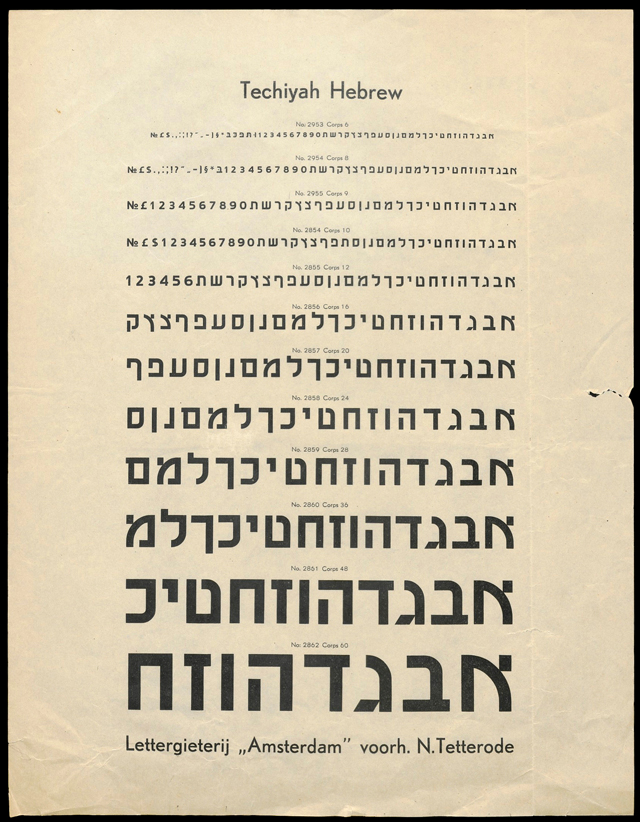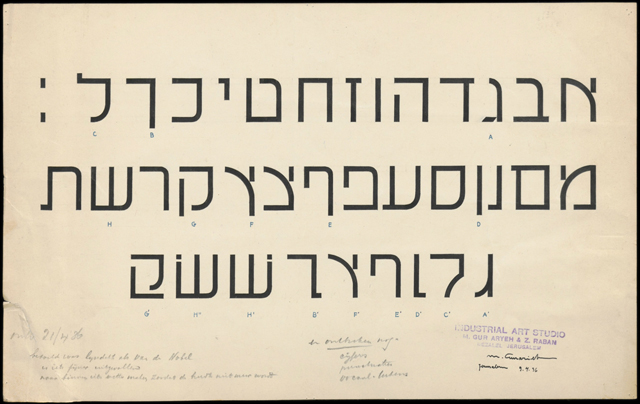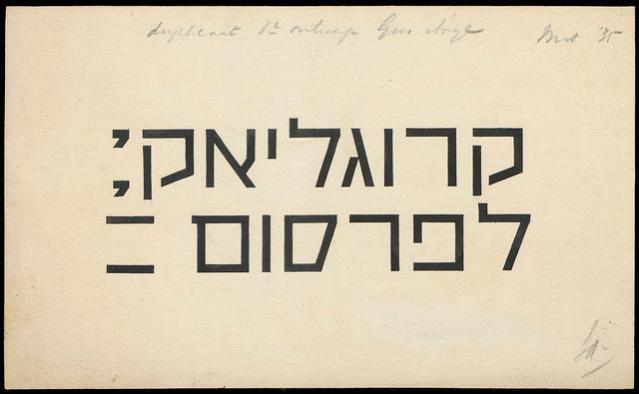
‹Techiyah Hebrew›
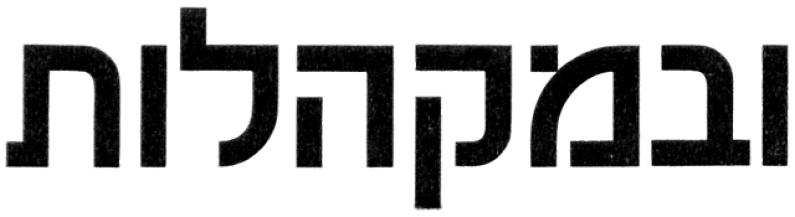
Mit der Typographischen Bibliothek der Schriftgiesserei «Amsterdam» (vormals «N. Tetterode») besitzt die Universitätsbibliothek Amsterdam (UvA) bereits seit 1971 eine bedeutende Sondersammlung zum Thema Druckschrift. 2010 übernahm die UvA dann auch das Produktionsarchiv der Firma aus den Jahren 1907–1977. Dieser Bestand wurde in den letzten Jahren komplett digitalisiert. Im «Archief Letterproductie van Lettergieterij ‹Amsterdam›» finden sich Spuren der Entwurfsprozesse einer Reihe bedeutender, für die Schriftgiesserei tätiger Gestalter wie Sjoerd H. de Roos, Jan Tschichold, Imre Reiner oder Roger Excoffon. Neben deren bekannten Entwürfen finden sich aber auch solche, die nie veröffentlicht wurden. Ein solcher ist der für eine konstruierte hebräische Serifenlose mit dem Namen Techyiah (Wiedergeburt), mit der die Schriftgiesserei Mitte der 1930er Jahre auf den neuen jüdischen Markt in Palästina abgezielt hatte.
(UvA) UBA519/168 [0025]: Techyiah Hebrew, Schriftmuster, o.D.
Mit der Ausarbeitung der Schrift war in Amsterdam Dick Dooijes betraut. Dooijes war zu diesem Zeitpunkt bei der Schriftgiesserei als Assistent von S. H. de Roos tätig und zeichnete bereits für eine Reihe von Schriften verantwortlich. Dooijes erwähnt das Projekt in seiner Autobiographie Mijn leven met letters (Amsterdam, 1991). Hier schreibt er, wie die Produktion bereits in Angriff genommen worden war, aber der Ausbruch des Weltkriegs 1939 die Handelsbeziehungen zu den potentiellen Abnehmern in Palästina verunmöglicht und dazu geführte hatte, dass die Schrift schliesslich in der Schublade verschwand. Die nun in digitaler Form zugänglichen Dokumente zeigen, dass das Projekt tatsächlich bereits weit gediehen war. Doijes hatte die Techyiah in zwölf Grössen gezeichnet sowie passende Ziffern, Interpunktions-, und Sonderzeichen entworfen. Aus den nun zugänglichen Dokumenten geht aber auch hervor, dass Dooijes – was er in seinen Erinnerungen unerwähnt lässt – keineswegs allein für den Entwurf verantwortlich war. Massgebliche Impulse kamen vom Jerusalemer Maler und Grafiker Meir Gur-Aryeh [Gur-Arie]. Von Gur-Aryeh stammen wohl nicht nur die ursprünglichen Entwürfe, er kommentierte auch kritisch die weitere Ausarbeitung derselben durch Doijes. Gur-Aryeh war kein Schriftgestalter, aber er war bestens vertraut mit den zeitgenössischen Versuchen im Bereich der hebräischen Gebrauchsgrafik, die Ästhetik der damals modischen «elementaren» lateinische Schriften auch auf das hebräische Schriftsystem anzuwenden.
(UvA) UBA519/170 [0019]: Erster Entwurf zur Schrift von Meir Gur-Aryeh, 1935
(UvA) UBA519/171 [0001]: Zweiter Entwurf von Gur-Aryeh, 1936
Im Bereich der Druckschriften stand als entsprechende Auszeichnungsschrift vor 1935 nur eine einzige Schrift zur Verfügung – die aus geometrischen Elementen konstruierte Chaim. Ihr Schöpfer, der damals in Warschau tätige Grafiker Jan LeWitt, orientierte sich bei seinem Entwurf offenbar an den gezeichneten kyrillischen Schriften, die seit Mitte der 1920er Jahre von konstruktivistischen Gestaltern wie Alexander Rodschenko verwendet wurden. Auch wenn das durchgehend eckige Schriftbild der Chaim von Gur-Ariyeh und Dojies um einige gezielt gesetzte Rundelemente ergänzt wurde, stellt LeWitts Schrift zweifellos den wichtigsten Ausgangspunkt für den Entwurf der Techyiah dar. So findet sich im Bestand u. a. auch ein Muster aus der Warschauer Schriftgiesserei Jan Idżkowski i S-ka, für die Chaim ursprünglich gezeichnet wurde. Wie der hebräische Stempel mit dem Namen des Generalvertreters für «Erez Israel» verrät, erreichte der Katalog aus Warschau Amsterdam via Palästina.
(UvA) UBA519/169 [0021]: Chaim, Schriftmuster, um 1930